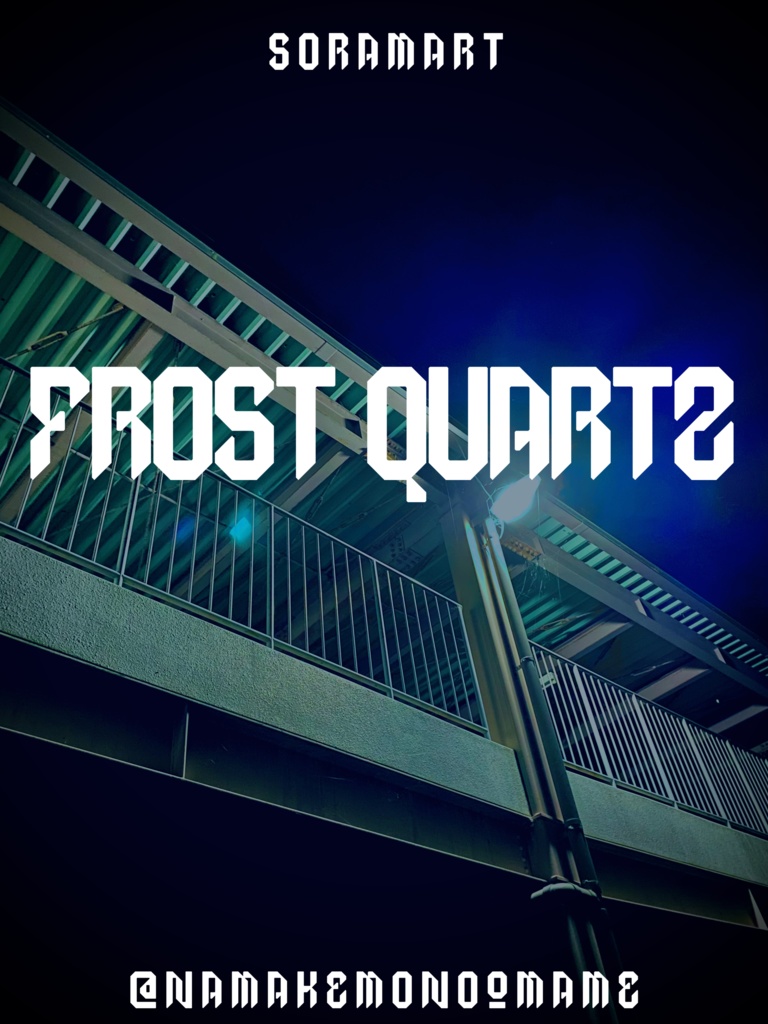
そらマートフォントデータ”Frost Quartz”Digital2,500 JPY放入購物車Buy a GiftAbout Gift氷をイメージした斜線モチーフのフォント "Frost Quartz" です。 「TrueTypeフォントファイル」という形式です。 ダウンロードした後、Zipファイル内のデータをインストールしてお使いください。 このフォントは商用利用可となっております。 お客様の制作・創作活動のお役に立てれば幸いです。 ※使用上の注意事項などは、添付のReadmeをお読みください。そらマートVisit FANBOX!Fontsフォントデータ詰め合わせ2025そらマート0 JPYFontsフォントデータ”Jumping Meteor Drop”そらマート2,500 JPYFontsフォントデータ”Jumping Meteor Wide”そらマート0 JPYFontsフォントデータ”Jumping Meteor”そらマート0 JPYFontsフォントデータ”Ragtime Key Tall”そらマート2,500 JPYFontsフォントデータ”Ragtime Key Bold”そらマート2,500 JPYFontsフォントデータ”Ragtime Key”そらマート2,500 JPYFontsフォントデータ”Cocoon Bullet Emerge”そらマート2,500 JPYFontsフォントデータ”Cocoon Bullet Slug”そらマート2,500 JPYFontsフォントデータ”Cocoon Bullet”そらマート2,500 JPYFontsフォントデータ”Frost Quartz Wide”そらマート2,500 JPYFontsフォントデータ”Frost Quartz LL”そらマート2,500 JPYFontsフォントデータ”Highway Surfer Loud”そらマート2,500 JPYFontsフォントデータ”Highway Surfer Long Leg”そらマート2,500 JPYFontsフォントデータ”Highway Surfer”そらマート2,500 JPYFontsフォントデータ”Marionette Papillon Super Wide”そらマート2,500 JPYFontsフォントデータ”Marionette Papillon Wide”そらマート2,500 JPYFontsフォントデータ”Marionette Papillon”そらマート2,500 JPYFontsフォントデータ”Bolted Bonito Brick”そらマート2,500 JPYFontsフォントデータ”Bolted Bonito Bold”そらマート2,500 JPY查看更多